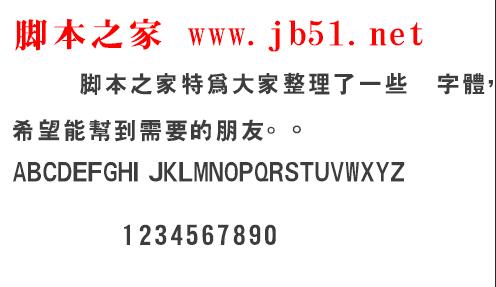
全真特黑體字體是由全真字庫(kù)開(kāi)發(fā)的一款經(jīng)典的黑體字體,該字體是黑體字體的風(fēng)格借鑒版,字型干練利落,具有時(shí)代鮮明特點(diǎn),吸收傳統(tǒng)中國(guó)書(shū)法的優(yōu)點(diǎn),做到保真、美感俱佳,具有很好的視覺(jué)感,且字庫(kù)完整,可以很好的應(yīng)用于文本裝潢、信息展示、網(wǎng)頁(yè)設(shè)計(jì)、篆刻制模、數(shù)據(jù)制作、裝潢設(shè)計(jì)、計(jì)算藝術(shù)設(shè)計(jì)、視覺(jué)設(shè)計(jì)、字帖等一切合法應(yīng)用場(chǎng)景,有喜歡的朋友可免費(fèi)下載收藏。